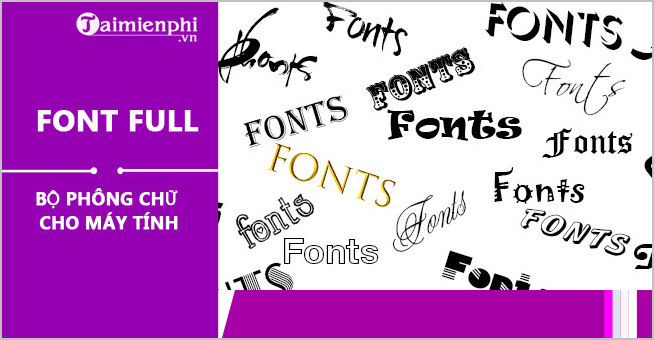
Bộ Font Full cung cấp hơn 800 phông chữ đa dạng, hỗ trợ tiếng Việt trên nhiều hệ điều hành, giúp bạn giải quyết vấn đề lỗi font khi soạn thảo văn bản hoặc thiết kế đồ họa. Bộ Font full bao gồm nhiều kiểu chữ, phù hợp với những ai yêu thích sự sáng tạo và cần sự linh hoạt trong việc lựa chọn phông chữ.
Tổng hợp Font chữ tiếng việt đẹp và đầy đủ dành cho máy tính
Font Full là bộ sưu tập các phông chữ đầy đủ dành cho máy tính, hỗ trợ nhiều loại font chữ tiếng Việt và tiếng Anh. Với hơn 800 phông chữ khác nhau, bao gồm cả các bảng mã Unicode, VNI, TCVN3, Font VNI và Font UTM, người dùng có thể thoải mái chọn lựa và sử dụng để soạn thảo văn bản hay tạo dựng thiết kế đồ họa. Không cần phải cài đặt từng font một, với chúng, bạn sẽ có ngay một kho phông chữ phong phú để sử dụng cho mọi công việc của mình.
Bộ Font Full này phù hợp cho nhiều công việc khác nhau, từ soạn thảo văn bản trong các phần mềm như Word, đến việc tạo chữ nghệ thuật trong Photoshop hay các phần mềm thiết kế khác. Với sự đa dạng về kiểu dáng, từ những phông chữ truyền thống như Times New Roman, Arial, đến các font nghệ thuật như thư pháp, một công cụ không thể thiếu cho những người làm việc với văn bản.
Trọn bộ font chữ tiếng Việt dành cho người dùng mày tính
Những đặc điểm nổi bật
- Hỗ trợ nhiều kiểu font tiếng Việt và Anh
Bộ phông chữ mang đến sự đa dạng về kiểu chữ, bao gồm font thư pháp, font nét bút, font TCVN3, VNI, Unicode... Phù hợp với nhiều đối tượng người dùng, từ những người yêu thích chữ nghệ thuật đến những người cần các phông chữ đơn giản cho công việc văn phòng.
- Khả năng tương thích trên nhiều hệ điều hành
- Cung cấp đầy đủ font cho công việc và sáng tạo
Với hơn 800 phông chữ, bộ sưu tập Full Font không chỉ phục vụ cho công việc soạn thảo văn bản mà còn đáp ứng tốt cho việc thiết kế đồ họa và tạo chữ nghệ thuật. Đặc biệt, chúng còn giúp người dùng tránh tình trạng lỗi font khi nhập văn bản hoặc sử dụng phần mềm thiết kế.